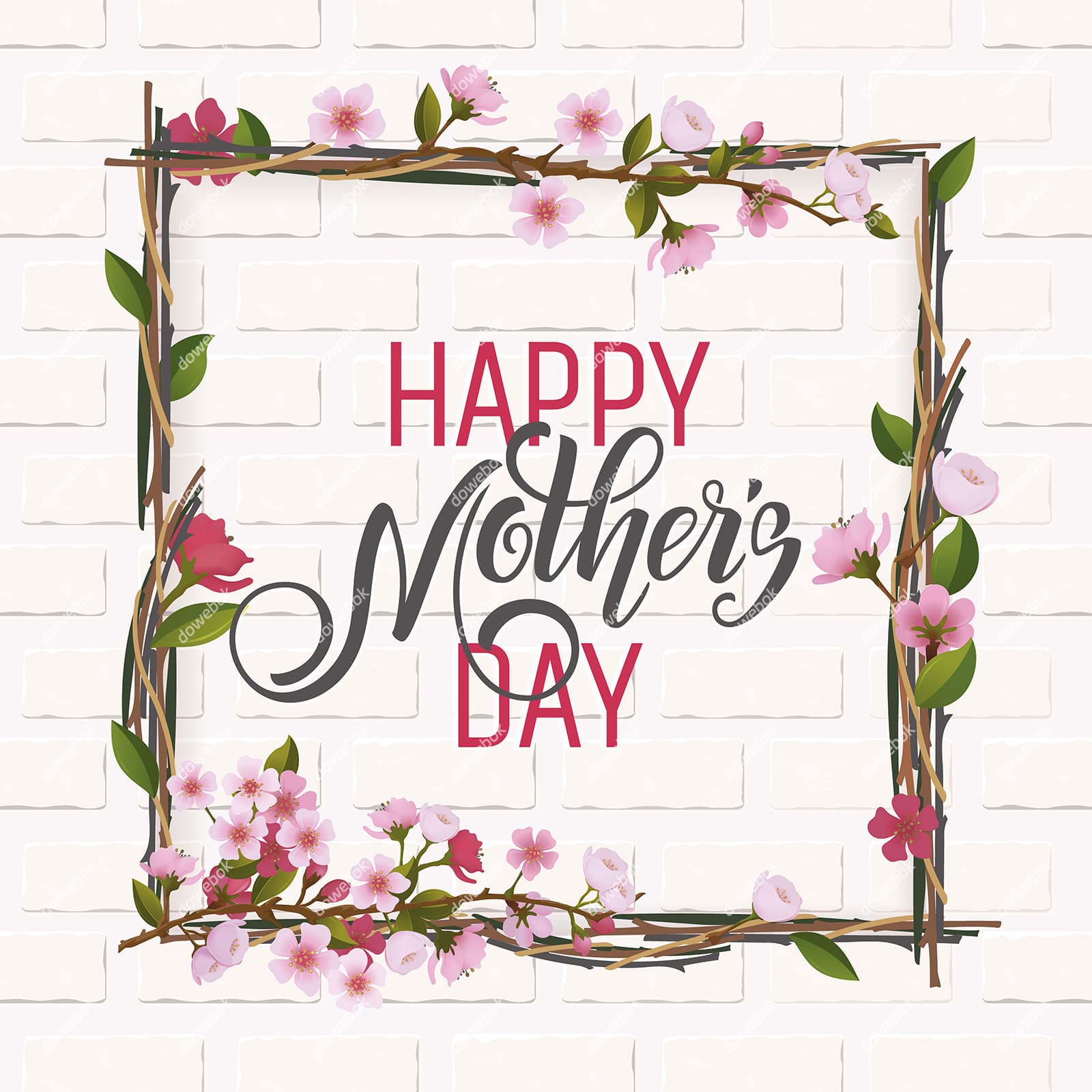
这是一款由花朵和 Happy Mother’s Day 字母设计母亲节图片素材,图片以白色砖墙为背景,中央有 “Happy Mother’s Day” 字样,“Happy” 与 “DAY” 为红色,“Mother’s” 是黑色手写体。文字外是树枝框架,装饰着粉色花朵与绿叶,色调柔和。整体营造出温馨氛围,传递出浓浓的母亲节祝福。